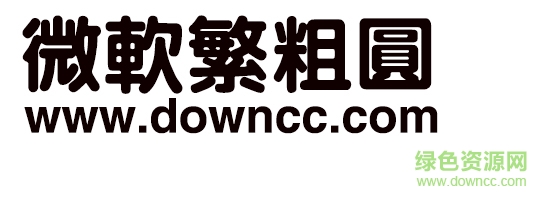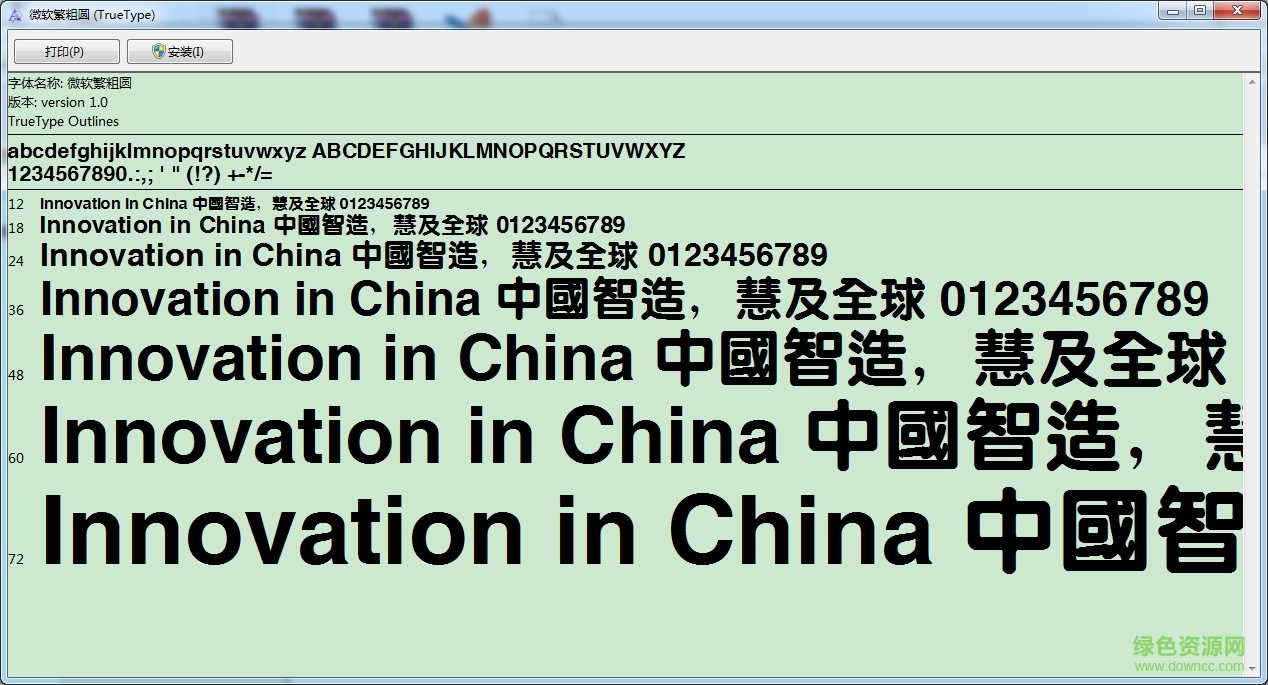
微軟繁粗圓字體風(fēng)格非常美觀。本字體可以用在平面廣告和印刷行業(yè)使用。字體形狀偏向粗壯化,讓繁體效果看起來更加有力度!歡迎用戶下載使用。
微軟繁粗圓是一款比較實(shí)用的粗體繁體字體,這款字體字形圓潤,看起來渾厚一體,非常適用于廣告設(shè)計(jì),喜歡這款字體的朋友可以來綠色資源網(wǎng)下載體驗(yàn)喲!